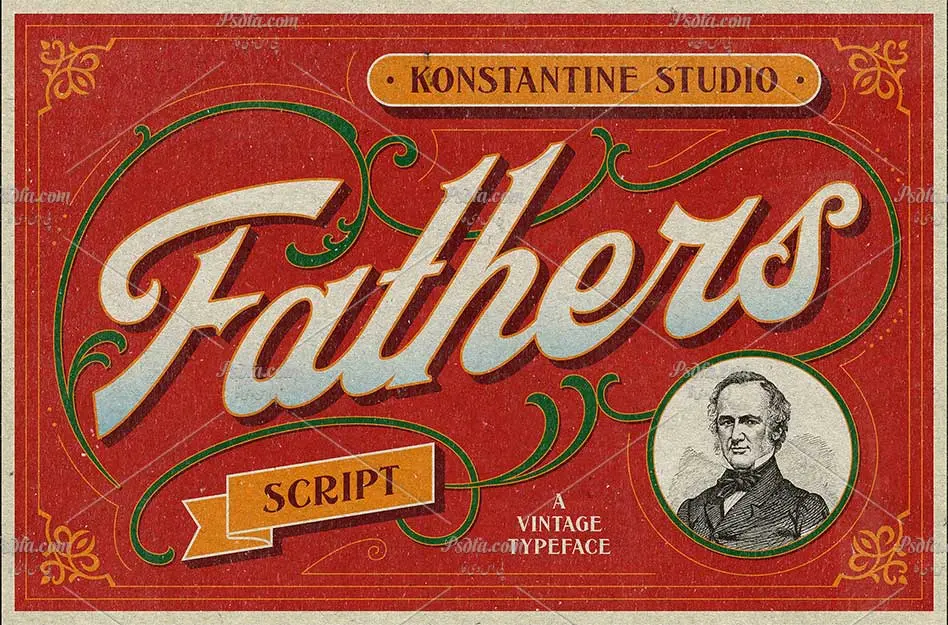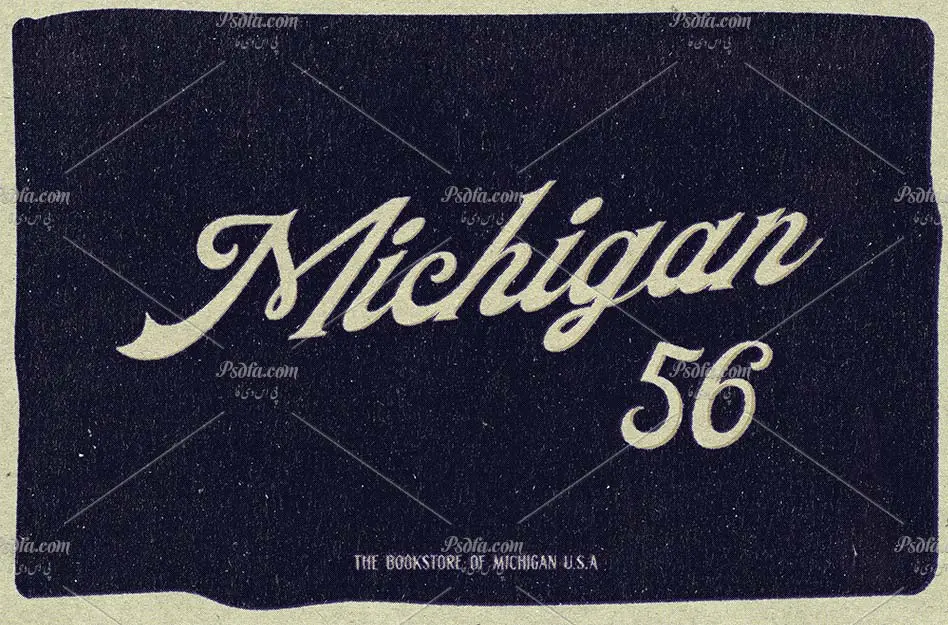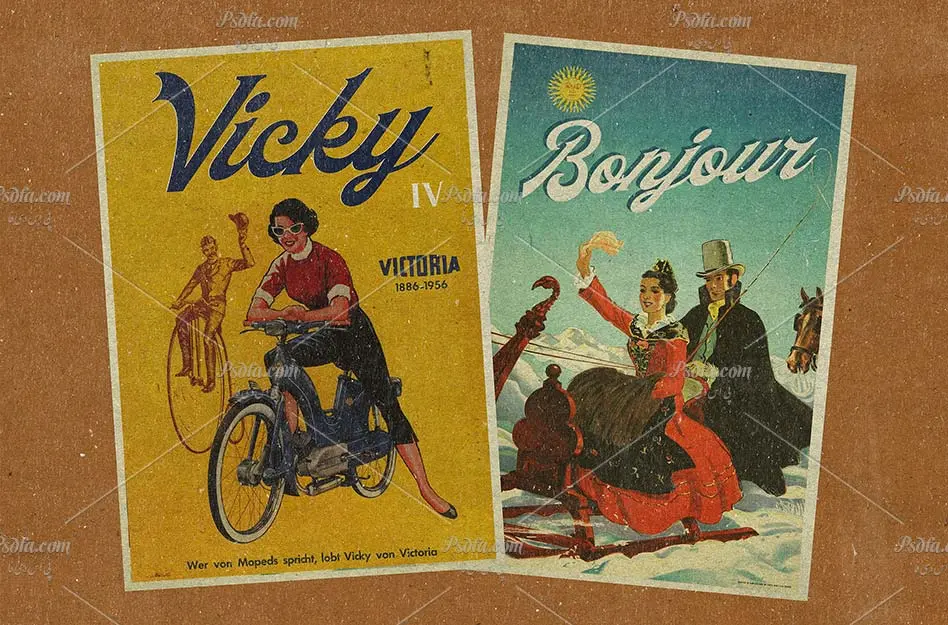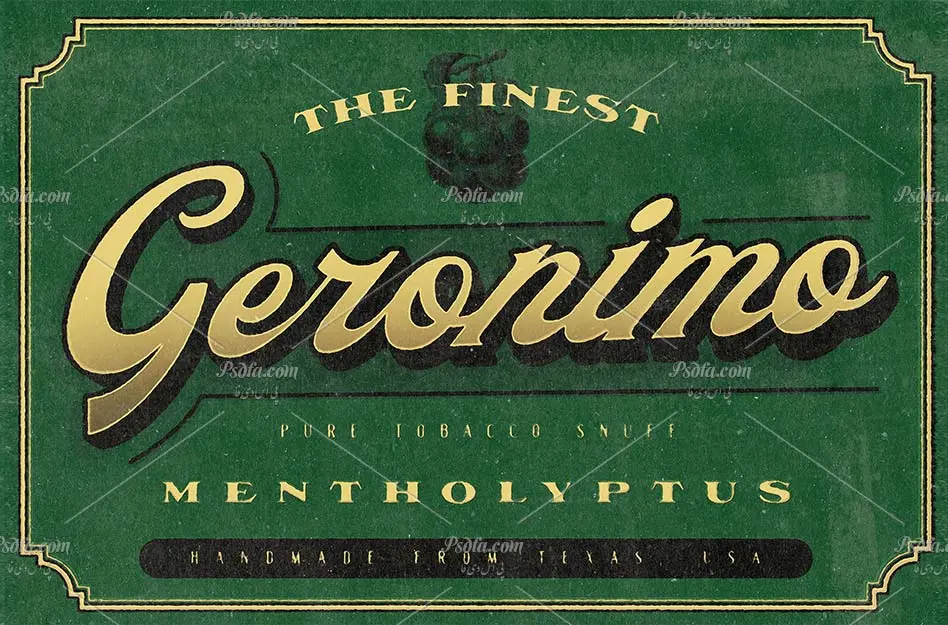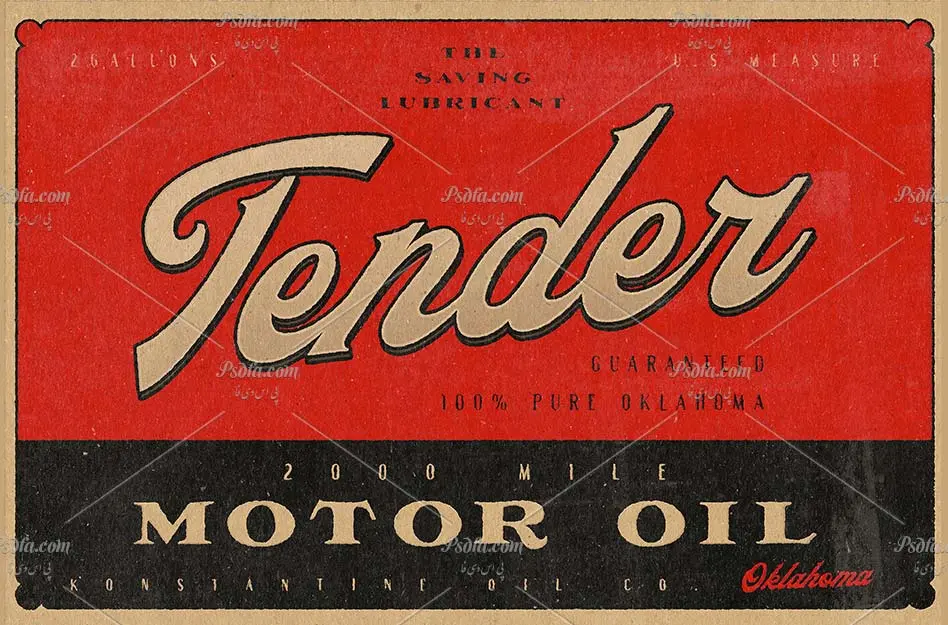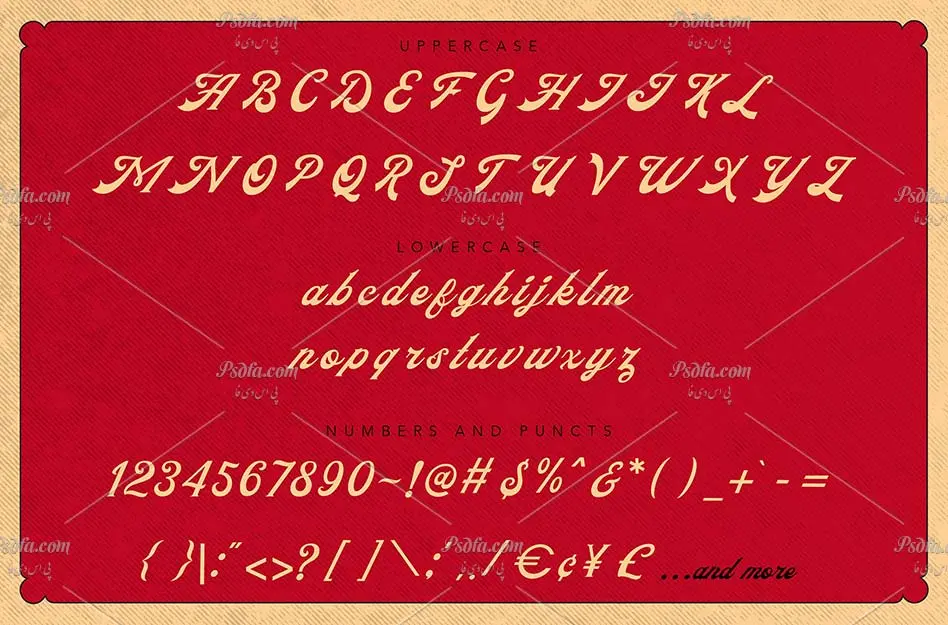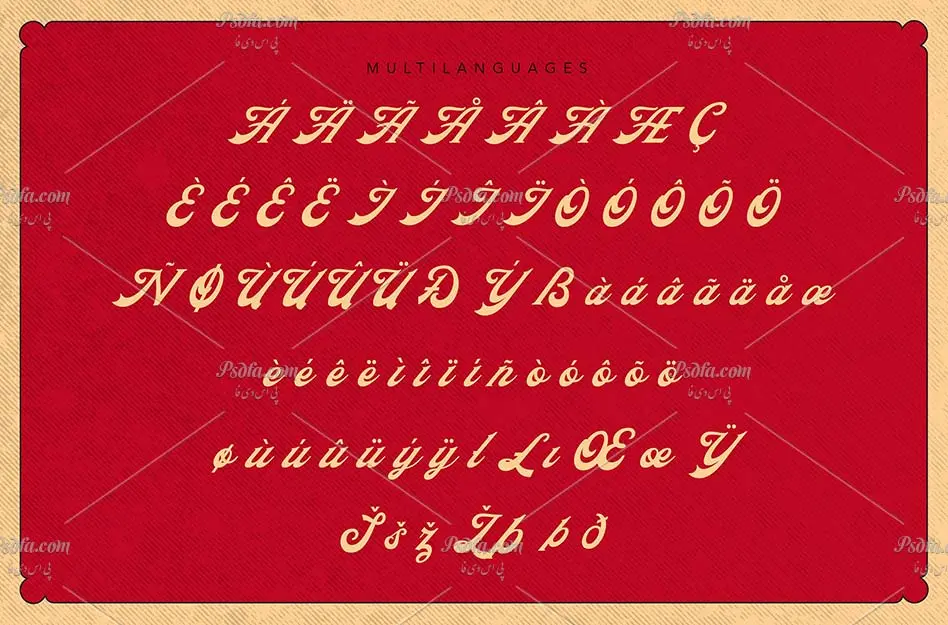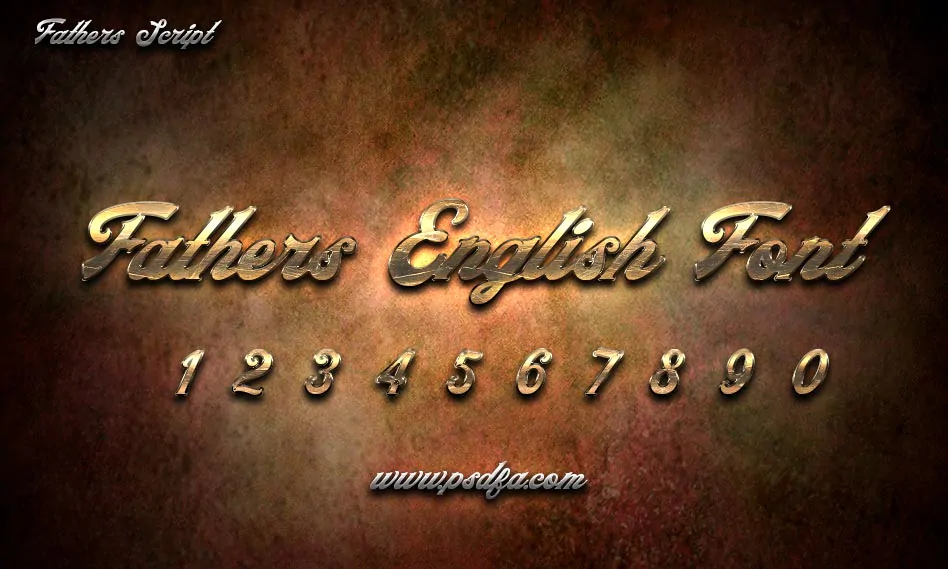
در این مطلب شاهد فونت انگلیسی Fathers در طرح و سبک فونت های قدیمی و گرانج می باشید. این فونت با فرمت otf در سایت قرار گرفته است که پس از نصب آن در سیستم ، می توانید از آن در تمام نرم افزارهای گرافیکی و ویرایشگر متن از جمله نرم افزار فتوشاپ ، مجموعه نرم افزار آفیس و … استفاده کنید. همانطور که ذکر شد استایل و حالت این فونت انگلیسی در طرح و سبک فونت های قدیمی می باشد که با استفاده از یک تکسچر و یا بافت گرانج می توانید به آن شکل و فرم خاصی بخشید. از این فونت زیبا می توان در موارد گوناگون از جمله طراحی و چاپ پوستر ، طراحی جلد کتاب ، طراحی بسته بندی محصولات و … استفاده نمود. پیش نمایش این فونت فوق العاده زیبا را می توانید در تصویر فوق و یا گالری تصاویر زیر مشاهده فرمائید.